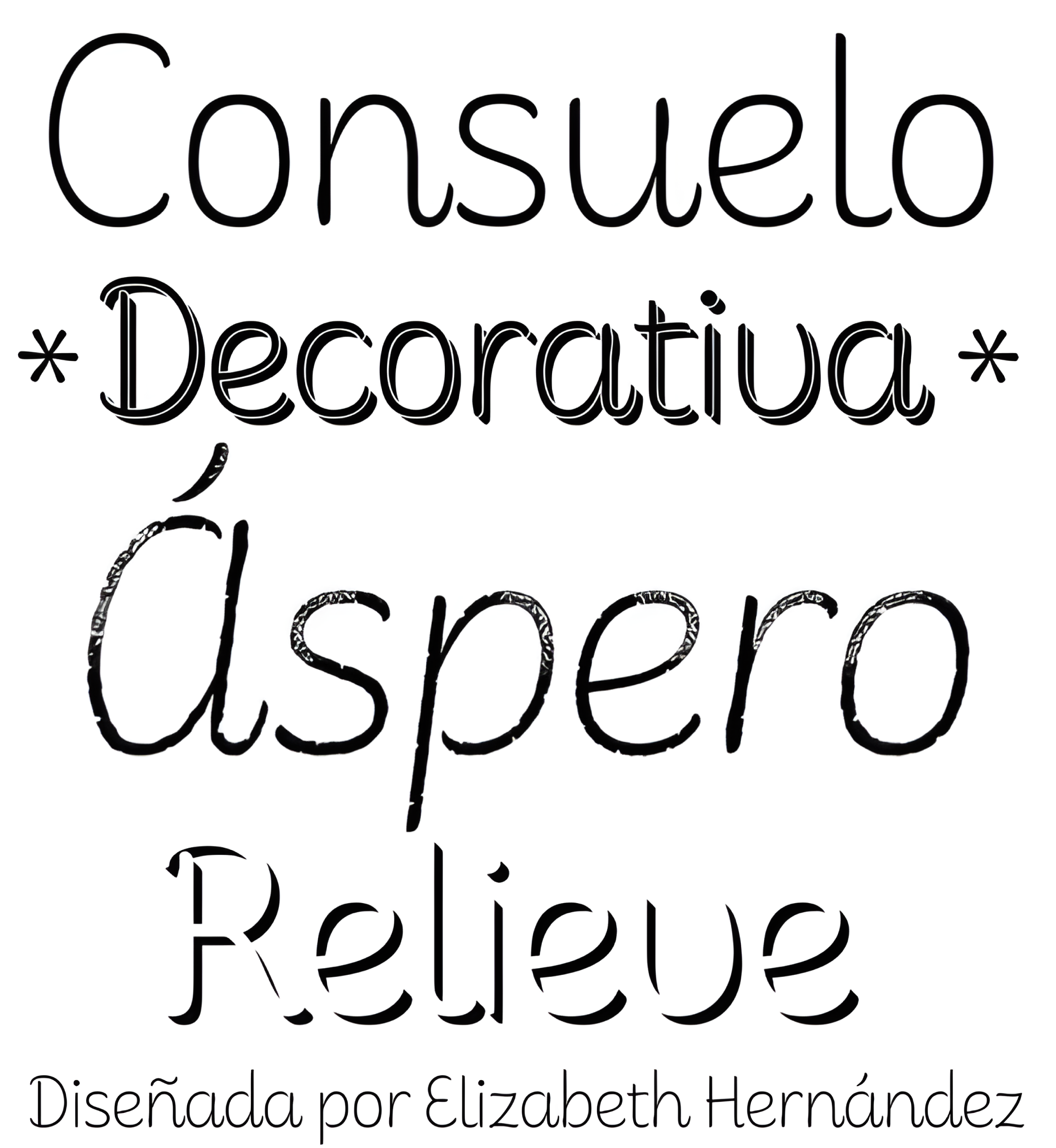
Consuelo
| Descripción | Consuelo es un tipo de letra inspirado en las pinceladas. La familia consta de un conjunto de 4 variantes, con sus respectivas cursivas, más un conjunto de ornamentos que darán al diseñador múltiples opciones a la hora de componer textos. Consuelo es ideal para su uso en títulos decorativos, frases cortas, revistas, logotipos y publicidad. |
| Familia(s) | Consuelo |
| Estilos | 9 |